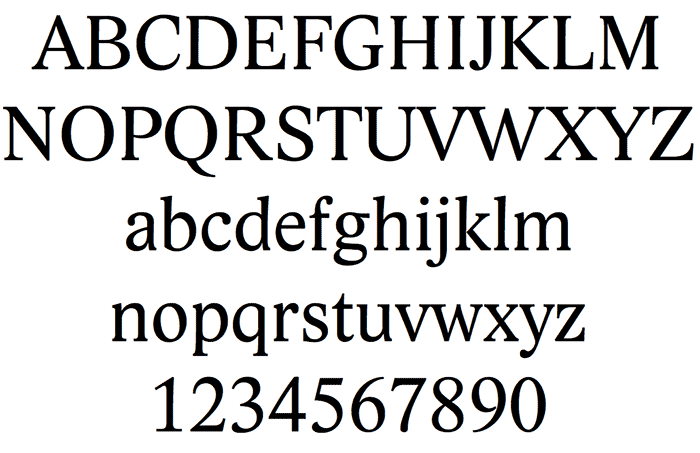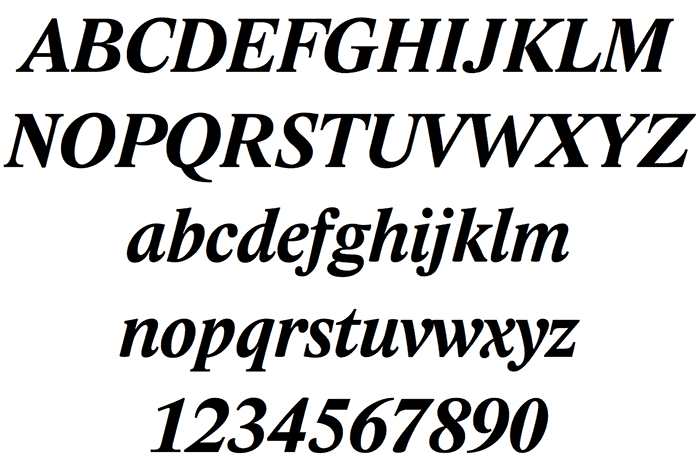
Lido STF 1.0
Die Lido STF von František Štorm entstand ursprünglich als eine modernisierte Version der Times für die tschechische »Volkszeitung« (Lidové noviny). Nachdem die Schrift schlussendlich jedoch nicht für die Zeitung eingesetzt wurde, baute Štorm die Schrift unabhängig vom ursprünglichen Auftraggeber weiter aus und bot sie in der Folge kostenlos zur privaten Nutzung an. Die Schrift besteht aus drei Strichstärken in zwei Weiten. In den normalen Weiten sind auch kursive Schnitte vorhanden.
František Štorm